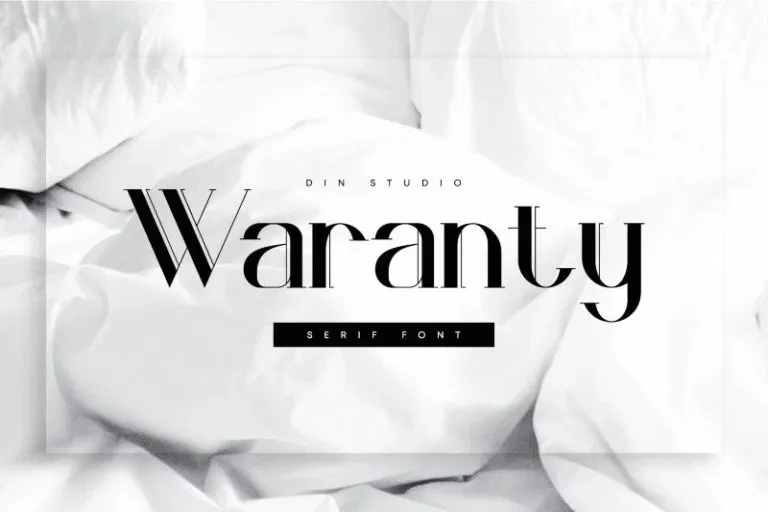
Waranty Font
Waranty Font é uma elegante serif que brota das linhas modernas do Din Studio, perfeitamente adaptada para qualquer projeto profissional que exija uma marca forte e sofisticada. Perfeita tanto para logos quanto para a criação de identidades visuais, essa fonte traz uma autêntica elegância às suas criações. Para quem busca um estilo clássico que se destaca em qualquer cenário, Waranty é um ótimo escolha, especialmente para as frases importantes ou citações que você deseja destacar em seu trabalho. Além de ser incrivelmente atraente e criativa, cada letra mantém sua singularidade, garantindo que sua identidade visual seja única. Uma verdadeira mão na massa para quem busca fontes sofisticadas para seus projetos profissionais.